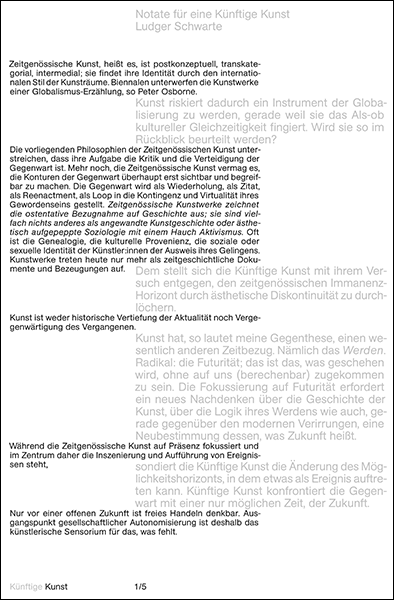
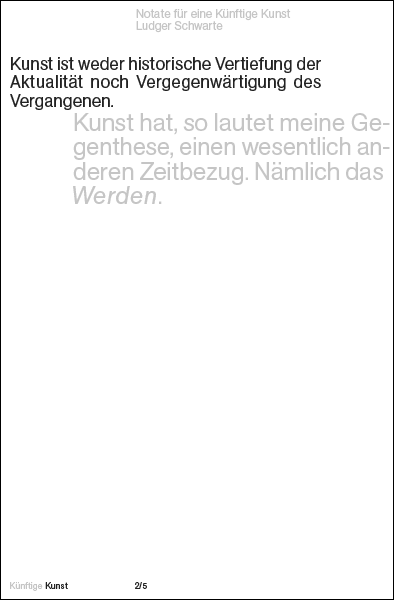
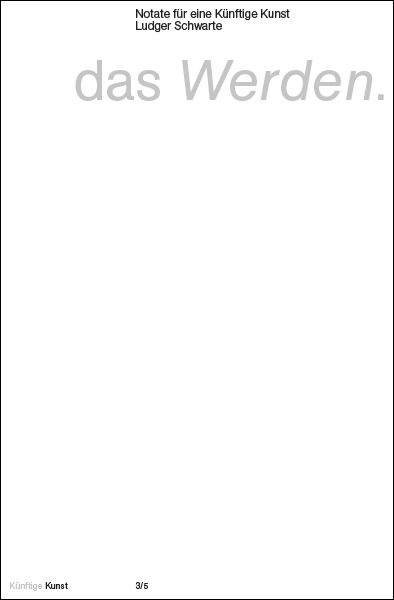
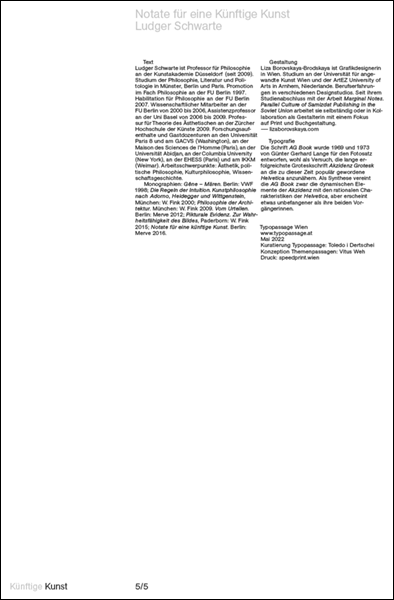
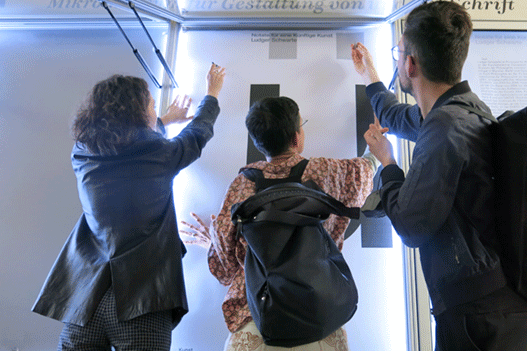
Typografie
Die Schrift AG Book wurde 1969 und 1973 von Günter Gerhard Lange für den Fotosatz entworfen, wohl als Versuch, die lange erfolgreichste Groteskschrift Akzidenz Grotesk an die zu dieser Zeit populär gewordene Helvetica anzunähern. Als Synthese vereint die AG Book zwar die dynamischen Elemente der Akzidenz mit den rationalen Charakteristiken der Helvetica, aber erscheint etwas unbefangener als ihre beiden Vorgängerinnen.